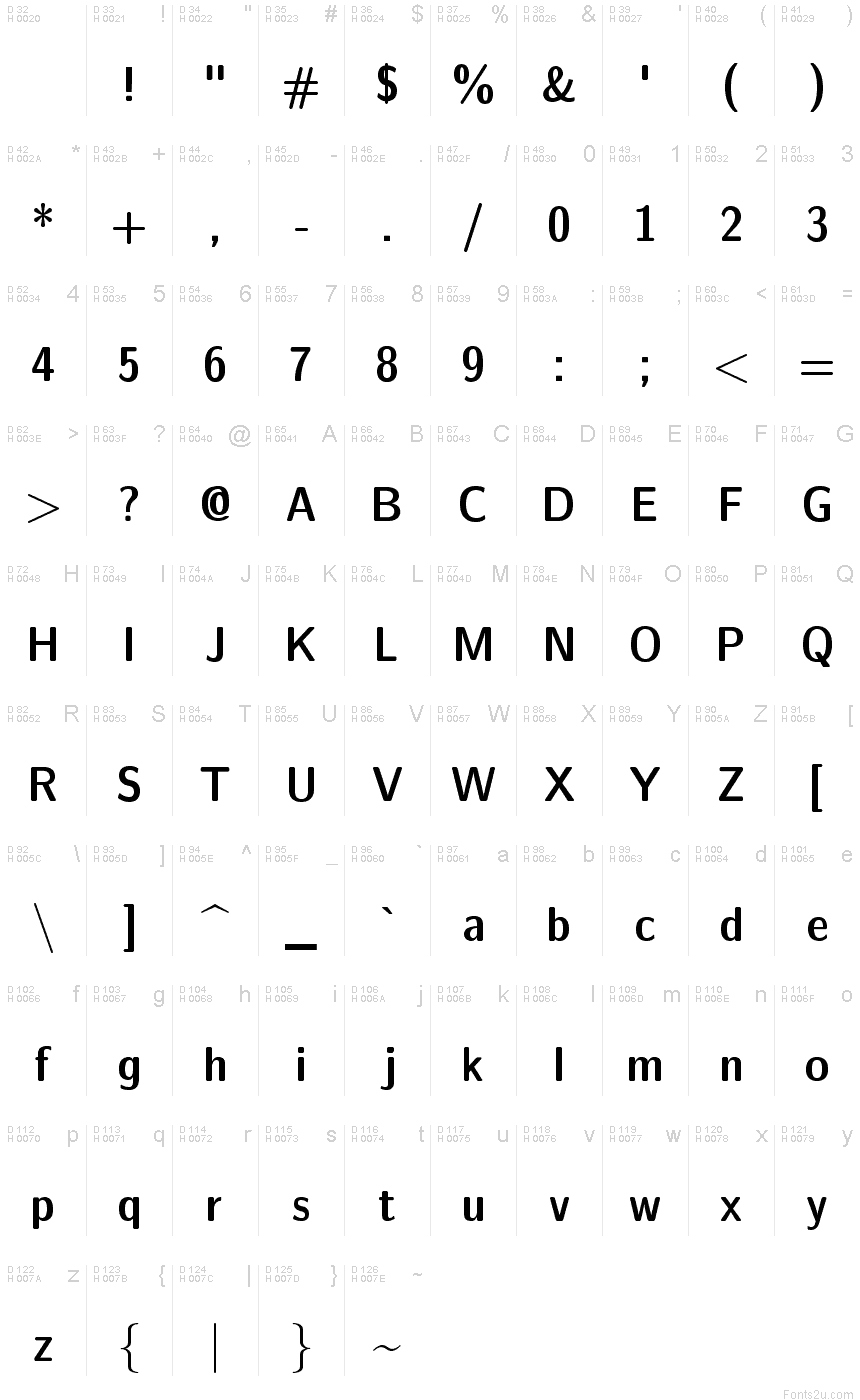
LM Sans Demi Cond 10, zaprojektowany przez B. Jackowskiego i J. M. Nowackiego, to darmowy, zwężony krój bezszeryfowy o zdecydowanych, oszczędnych formach. Jego pionowe kreski są proste i wyraziste, a łagodnie zaokrąglone łączenia zmiękczają zwartą budowę liter. Małe litery zachowują otwarty i bezpośredni charakter.
Czyste sylwetki znaków mogą nawiązywać do prostych ikon i elementów diagramów w publikacjach technicznych lub grafice cyfrowej. Zwarte proporcje sprawdzają się również w identyfikacji wizualnej oprogramowania oraz w oznakowaniu informacyjnym. We wszystkich tych zastosowaniach powściągliwy rysunek liter dobrze współgra z funkcjonalną grafiką.
LM Sans Demi Cond 10